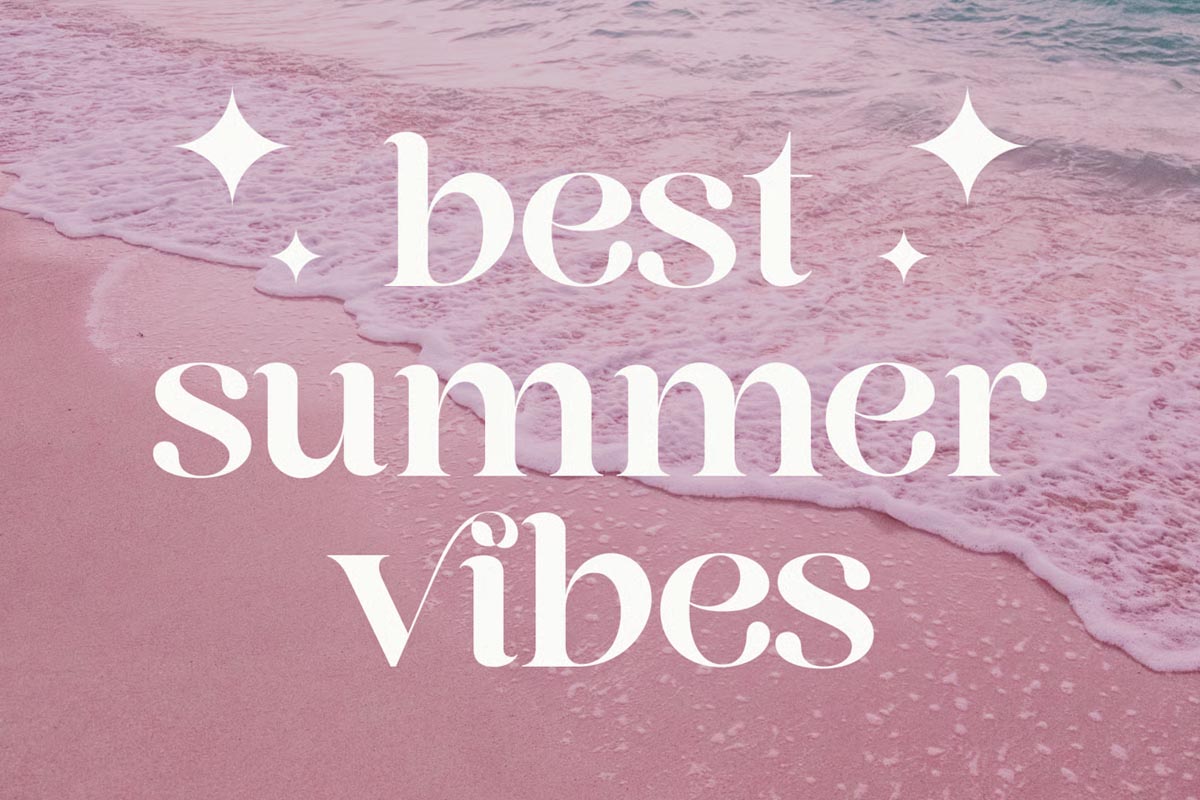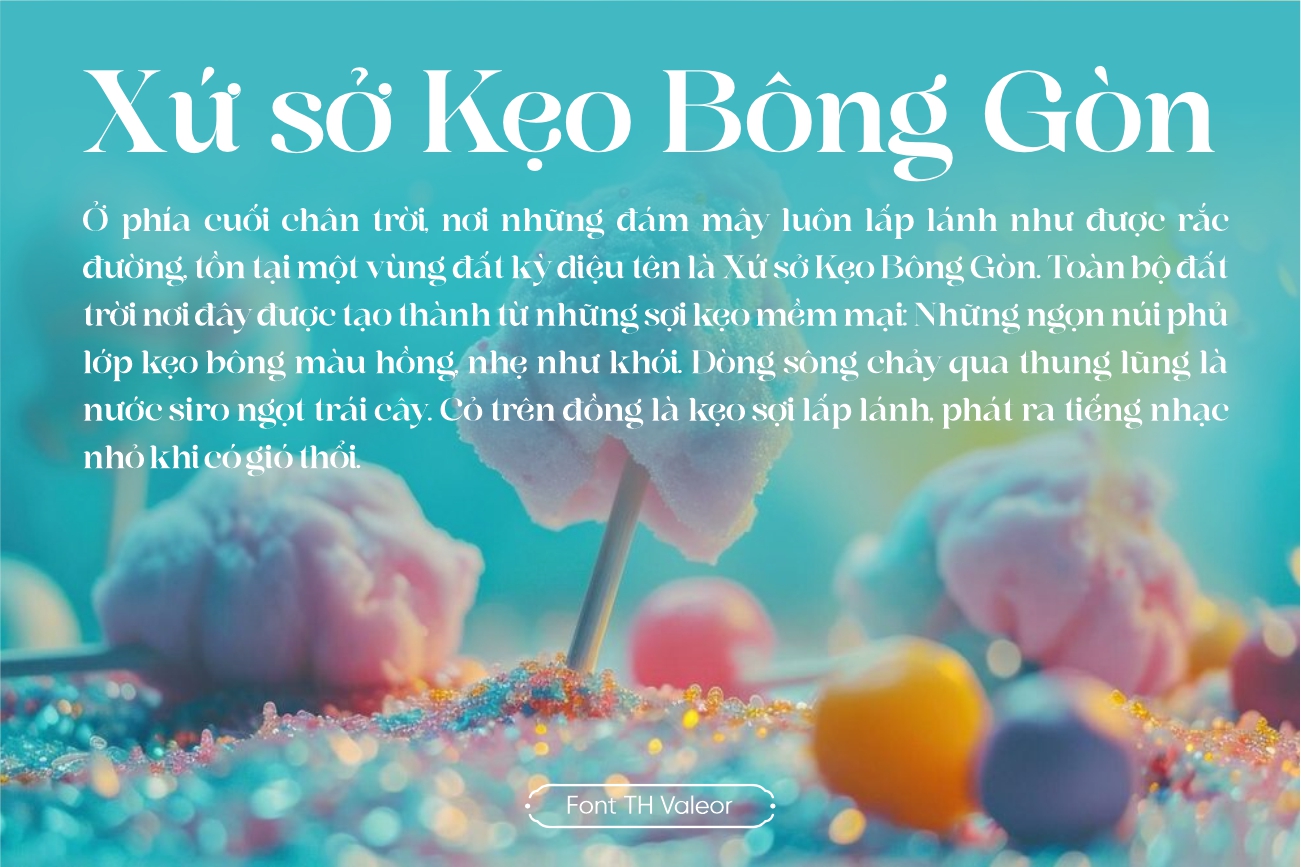
TH Valoer – Font Chữ Thẩm Mỹ Tuyệt Đẹp, Sang Trọng Mới Nhất
Tác giả Marva Design
Trong thế giới thiết kế đồ họa ngày nay, việc tìm kiếm một font chữ hiện đại mang đậm tính nghệ thuật là chìa khóa để tạo nên sự khác biệt cho thương hiệu. TH Valoer chính là câu trả lời hoàn hảo cho những nhà thiết kế đang theo đuổi phong cách sang trọng, tinh tế. Đây là dòng font Serif (có chân) nhưng được cách tân với những đường nét tương phản dày - mỏng đầy quyến rũ, tạo nên một tổng thể vừa hoài cổ lại vừa thời thượng, rất phù hợp với xu hướng thiết kế Minimalist (tối giản) và Luxury (sang trọng) hiện nay.
Điểm đặc biệt khiến TH Valoer trở thành sự lựa chọn hàng đầu cho các dự án nhận diện thương hiệu chính là tính chất "thanh lịch" tự nhiên của nó. Nếu bạn đang tìm kiếm một font spa để thiết kế logo, menu dịch vụ hay bảng hiệu cho các trung tâm thẩm mỹ, mỹ phẩm cao cấp, thì TH Valoer sẽ giúp truyền tải thông điệp về sự thư thái và đẳng cấp ngay từ cái nhìn đầu tiên. Những đường cong mềm mại kết hợp với chân chữ sắc sảo giúp tôn lên vẻ đẹp của sự chăm sóc và nâng niu, yếu tố cốt lõi của ngành làm đẹp.
Về nguồn gốc, bộ font này có tên gốc là Valoer, một sáng tạo tuyệt vời đến từ tác giả Marvadesign. Nhận thấy vẻ đẹp tiềm năng và nhu cầu sử dụng lớn tại thị trường Việt Nam, Team TH đã tiến hành Việt hóa trọn bộ, tinh chỉnh lại các dấu câu và đặt tên là TH Valoer. Nhờ công sức của đội ngũ Team TH, giờ đây các Designer Việt có thể thoải mái sáng tạo các ấn phẩm tiếng Việt mà không lo lỗi font, đảm bảo tính thẩm mỹ cao nhất cho mọi văn bản.
Không chỉ giới hạn ở lĩnh vực làm đẹp, TH Valoer còn được mệnh danh là font chữ thẩm mỹ đa năng. Dù bạn sử dụng để thiết kế thiệp cưới, bìa tạp chí thời trang, bao bì sản phẩm hay các bài đăng trên mạng xã hội, font chữ này đều mang lại hiệu ứng thị giác mạnh mẽ. Sự hiện diện của TH Valoer trong các thiết kế sẽ biến những dòng tiêu đề đơn điệu trở thành những tác phẩm nghệ thuật typography thực thụ, giúp nâng tầm giá trị thương hiệu của bạn lên một tầm cao mới.